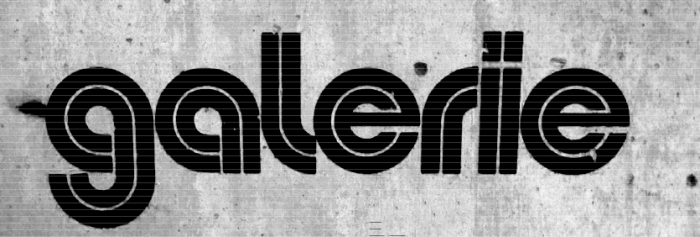
Suche ähnliche Schrift wie Pump triline / Kandel / Cressida
ich suche einen Schrifttyp das ähnlich aussieht wie Pump triline / Kandel / Cressida - nur der ist nicht in drei geteilt aber nur in zwei. Siehe bitte Anhang.
wenn es dir auf die »mehrlinigkeit« ankommt und nicht auf den eher bauhaus-mäßigen stil, dann schau dir mal die ryman eco an. noch dazu for free
Vielen Dank für deine Hilfe :-) Leider muss es genau den gleichen sein.